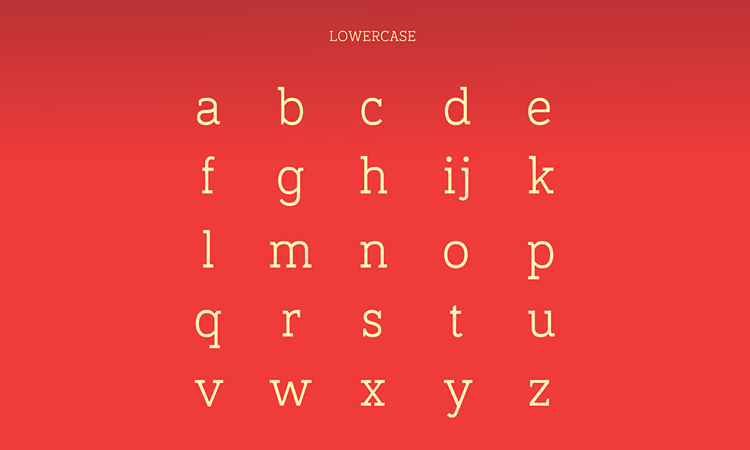
Umbraは、柔軟性のある、新しいスラブセリフのフォントです。スラブセリフは、セリフ(ひげ)の部分が文字の主線と同じ太さでデザインされたフォントのことです。産業革命により「広告」という新しいデザインの概念が登場し、遠目に見ても読みやすく、デザイン性もあるフォントが求められて誕生しました。Umbraは、セリフ(ひげ)の部分の角度が数学的に美しくデザインされた、モダンな仕上がりです。Webから印刷物まで、幅広く使うことができます。
大文字
小文字
数字
記号
フォントのサンプル
セリフの美しい角度が特徴